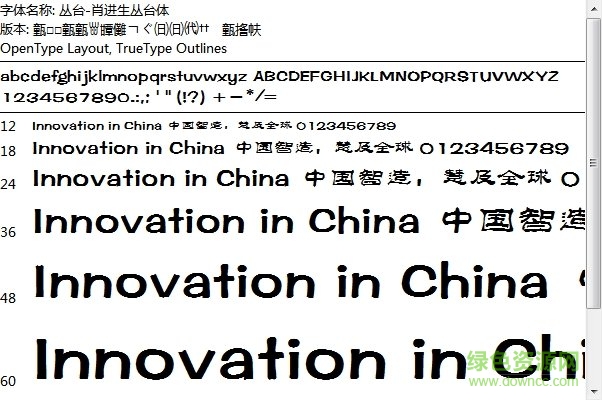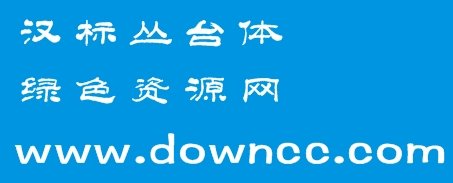
漢標(biāo)叢臺(tái)體字體
漢標(biāo)叢臺(tái)體是漢標(biāo)字體收錄的一款特色中文書法字體,由邯鄲肖進(jìn)叢創(chuàng)作,收錄在叢臺(tái)字庫、邯鄲字庫,整體效果較佳,字庫完整,能滿足大家的日常需求,綠色資源網(wǎng)獨(dú)家推薦!
叢臺(tái)肖進(jìn)生叢臺(tái)體特色
叢臺(tái)-肖進(jìn)生叢臺(tái)體
相關(guān)介紹